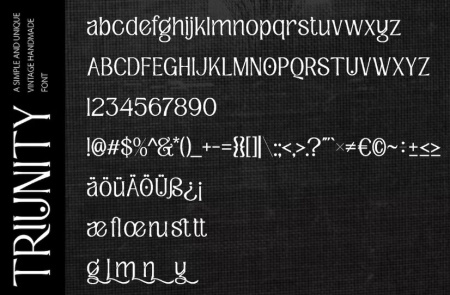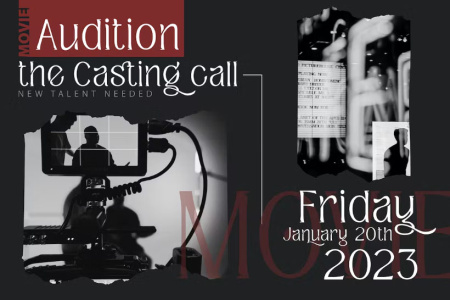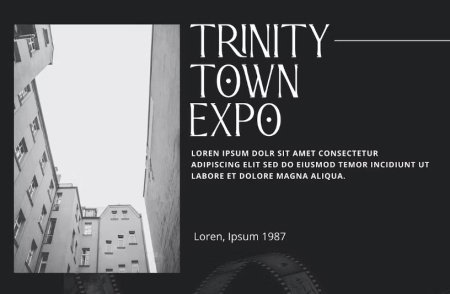
فونت جدیدی است که برای بسیاری از نیازهای بصری شما مانند دعوتنامه، کارت های تبریک، مواد برندسازی، کارت ویزیت، نقل قول ها، پوسترها و موارد دیگر معتبر و مناسب است! این فونت دارای ویژگی های Open Type مانند Styistic Sets، Stylistic Alternates و Ligature می باشد. ویژگی های Open Type را می توان با استفاده از برنامه های هوشمند Open Type مانند Adobe Illustrator، Adobe InDesign، Adobe Photoshop Corel Draw X و Microsoft Word مشاهده کرد. و این فونت یونیکد PUA (فونت های کدگذاری شده خاص) را داده است. به طوری که به راحتی می توان به تمام کاراکترهای جایگزین به طور کامل دسترسی داشت. برای دانلود فونت قدیمی Triunity از سایت gfx به ادامه مطلب مراجعه نمایید.
فونت انگلیسی قدیمی Triunity
دانلود فونت انگلیسی با تم قدیمی Triunity
فونت انگلیسی به سبک قدیمی Triunity
• شخصیت ویژه برای جایگزین ها و لیگاتورها
• فونت ها شامل پشتیبانی چند زبانه است